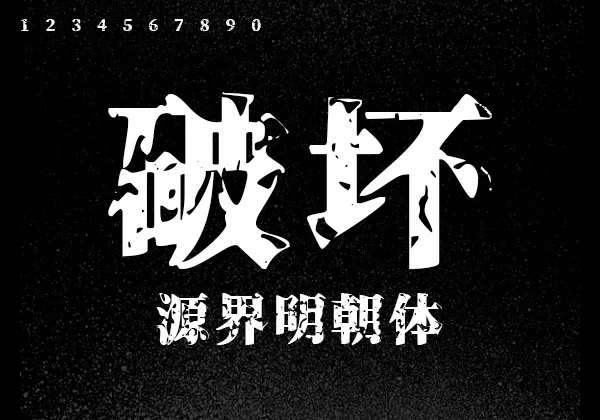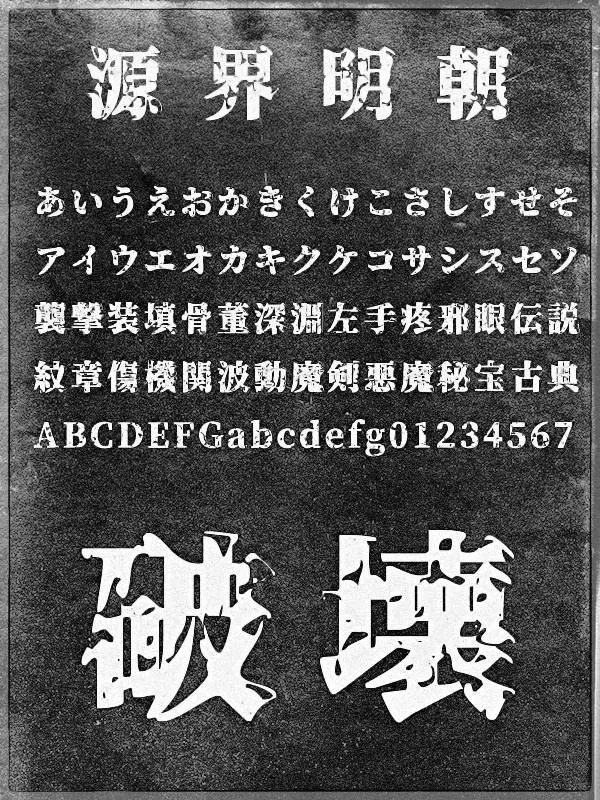
源界明朝字體, 是一款免費日文字型,以「思源宋體」(日文為「源ノ明朝」)為基礎,加入破壞效果使其最接近可讀狀態,據設計師說,字體具有很大的張力,他“扭曲”直到人眼幾乎不可讀, 但是,這樣可以表現出史詩般的戲劇感。
源界明朝字體具有相當大的張力,可作為圖片內的標題和大字使用,整體來說相當吸睛且頗具效果。